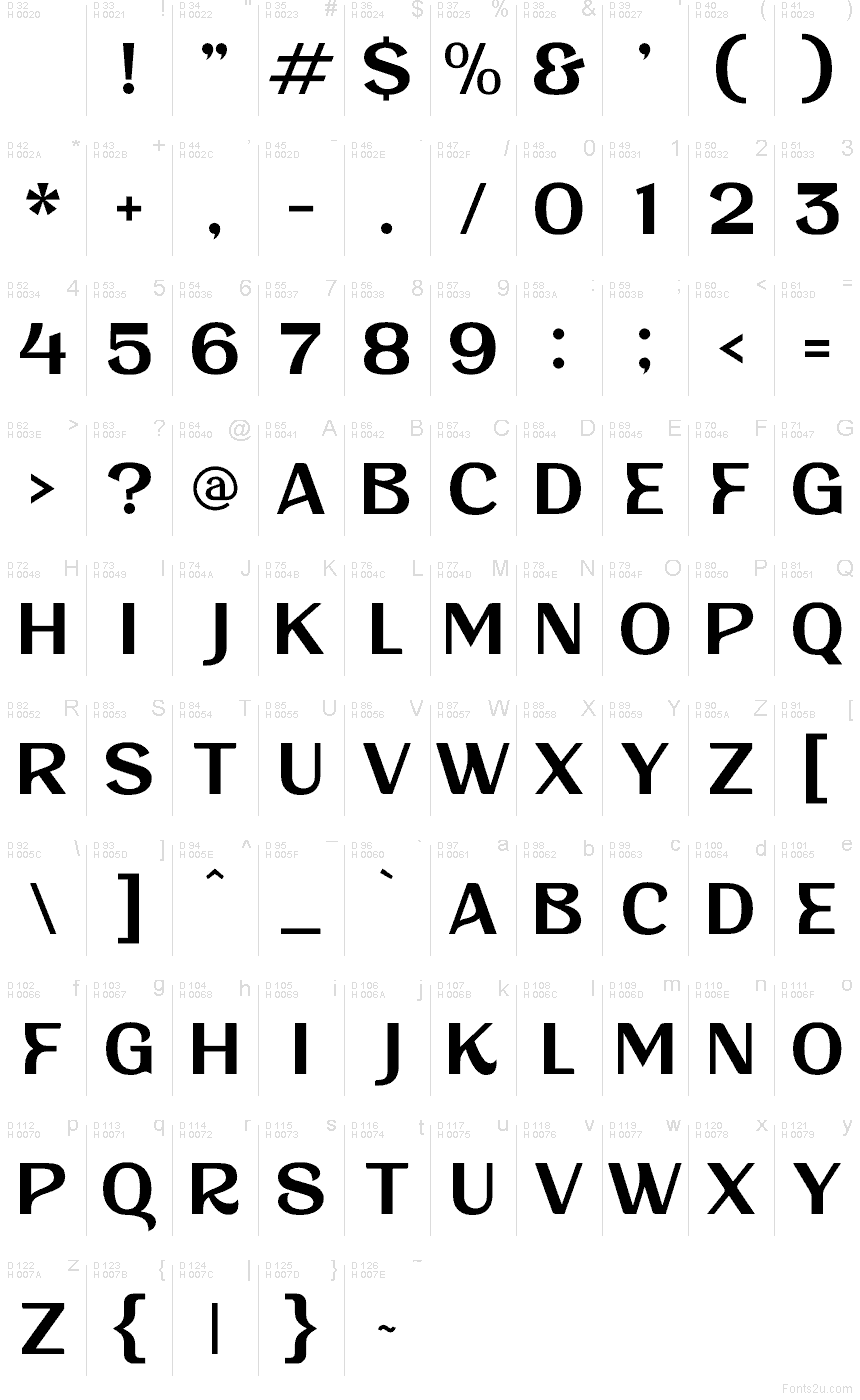
Belriner od Denustudios je bezplatné retro písmo typu display, které zaujme svými vysokými vertikálními tahy a širokými oblými křivkami. Ty dodávají písmenům plastický vzhled připomínající staré plakáty. Kombinace rovných dříků, hranatých zakončení a plynulých křivek zajišťuje, že si písmo zachovává estetiku vintage vývěsních štítů, namísto aby působilo jako další generický geometrický font.
Skvěle se hodí pro branding kaváren, přebaly alb, plakáty, obaly či grafiku výloh všude tam, kde potřebujete stylový a vzpřímený vzhled. Kompaktní struktura a propracované křivky dodávají krátkým nadpisům a logům osobitý rytmus, což je ideální pro projekty, které chtějí vdechnout designu nádech historie, aniž by působily příliš jako laciná dekorace.